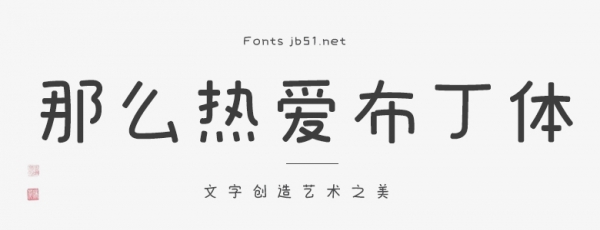
那么熱愛布丁體是由那么熱愛造字推出的一款手寫藝術(shù)字體,布丁體擺脫一般創(chuàng)作字形時(shí)的板正,字體更賦予靈動(dòng)性。字體筆畫由粗細(xì)不同的直線搭配而來, 折筆處呈圓角, 字體的中宮相對(duì)寬松。適用于包裝設(shè)計(jì)、電商、品牌名稱、漫畫、影視綜藝、游戲、各類商業(yè)海報(bào)、戶外廣告標(biāo)題等設(shè)計(jì)領(lǐng)域,歡迎喜歡此字體的朋友前來下載使用。